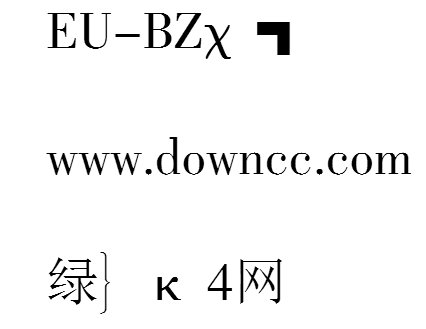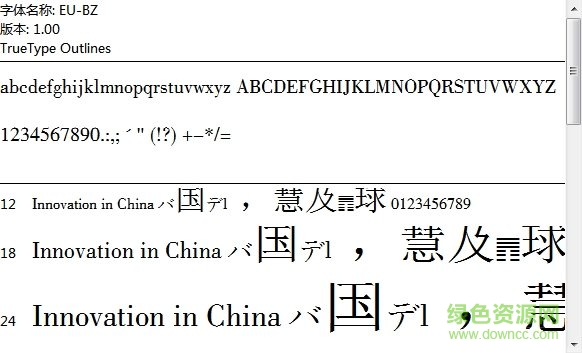
eu bz字體是一款造型十分迥異的方正字體,整體造型與eu bx字體比較類似,需要在日語輸入法下方能顯示,英文書寫比較突出,清晰醒目,如果你喜歡不妨來綠色資源網(wǎng)體驗哦!
eu bz字體共7545個字符,字符分布基本拉丁文,拉丁文-1補充,空白修飾字母,一般標點符號,似字母符號,箭頭等,有著十分廣泛的書寫效果。
eu bz字體即方正白正字體,可以用來編輯word文件的公式,是方正書版數(shù)字字體的其中之一,另一款稱為方正黑正字體,適合外文教材的打印和編輯,支持白斜字體等。